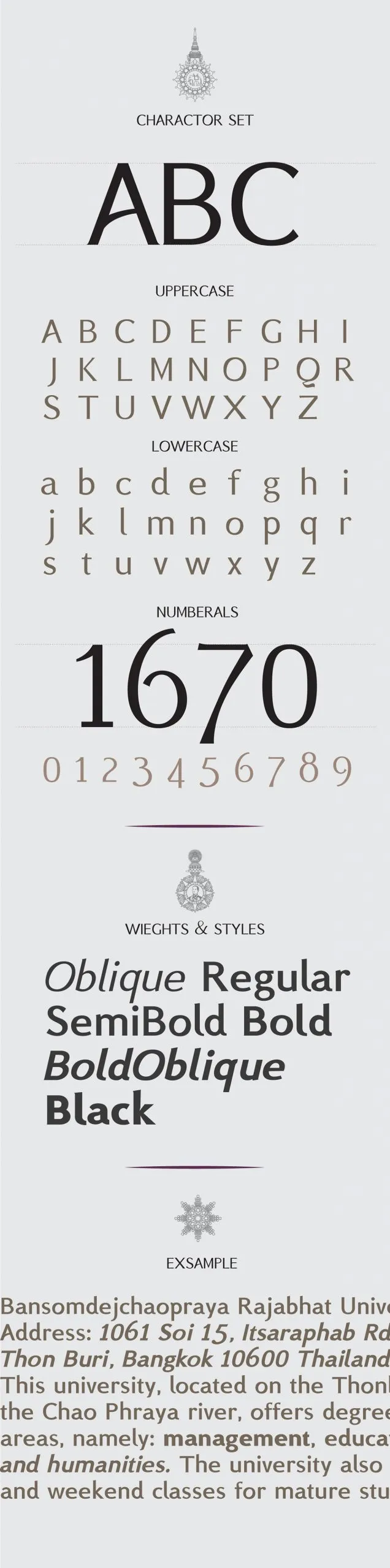
A BSRU-Bansomdej [V.2.0] é uma tipografia sem serif inspirada na estética clássica tailandesa contemporânea. Este tipo de fonte apresenta múltiplas alternativas para pesos e estilos, totalizando 10 opções. Perfeita para uso em cabeçalhos de posters e texto principal (incluso o alfabeto latino), essa BSRU-Bansomdej é ideal para criar gráficos impactantes que combinam elegância com modernidade. Ideal tanto para aplicativos digitais quanto para impressão, a BSRU-Bansomdej oferece uma paleta de possibilidades que se adequa perfeitamente à sua necessidade criativa.